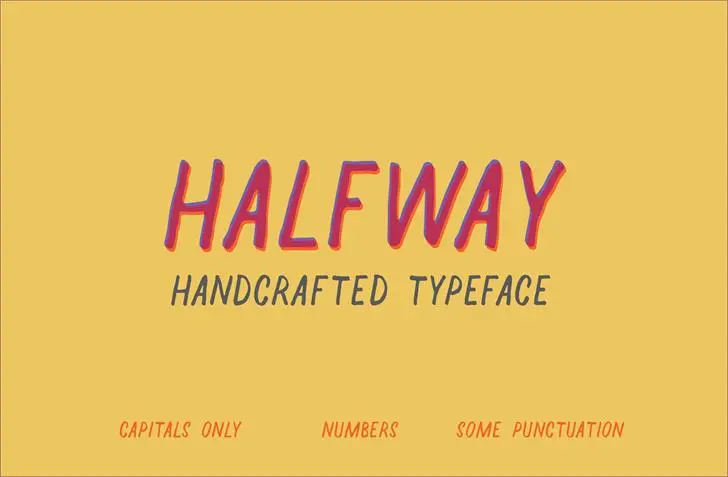
A Halfway font é uma grata surpresa para os fãs do estilo handwritten que buscam algo único e versátil para seu projeto. Desenhada pelo talentoso Hamilton, esta font oferece um toque de autenticidade única que faz com ela seja perfeita tanto para criações pessoais quanto corporativas. Com uma forma levemente deslendada e expressiva, a Halfway captura as sutilezas da escrita manuscrita real, permitindo que os designers façam sua própria interpretação ao criar textos elegantes e únicos. Esta font é uma excelente escolha para quem busca um toque pessoal em seus materiais digitais ou impressos. Ela traz a sensação de confidencialidade e personalização que fazem do seu design tão especial. Seja você criando cartões de visita, projetando produtos em linha ou simplesmente adicionando um toque autêntico a sua página da web, a Halfway font certamente fará uma grande diferença.